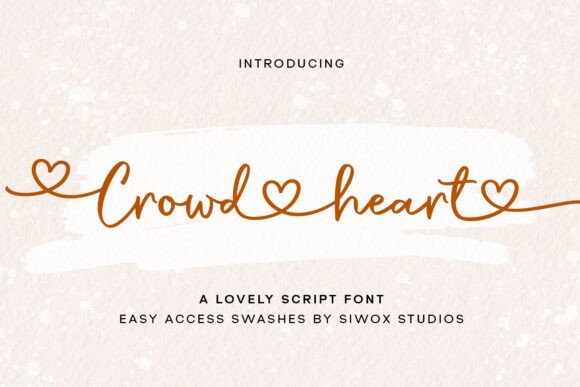
Crowd Heart Script
Поиск подходящих элементов дизайна может быть сложным, но Crowd Heart Script предлагает исключительную коллекцию, которая мгновенно улучшит вашу работу.
Созданный с высокой точностью, Crowd Heart Script предоставляет чистые векторы, плавную типографику и коммерческую лицензию для вашего спокойствия.
Создаете ли вы продукты POD (печать по требованию), свадебные приглашения или графику для социальных сетей, Crowd Heart Script станет идеальным выбором.